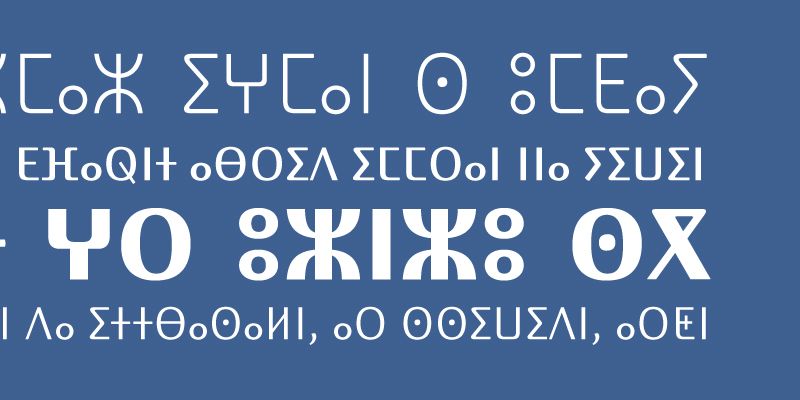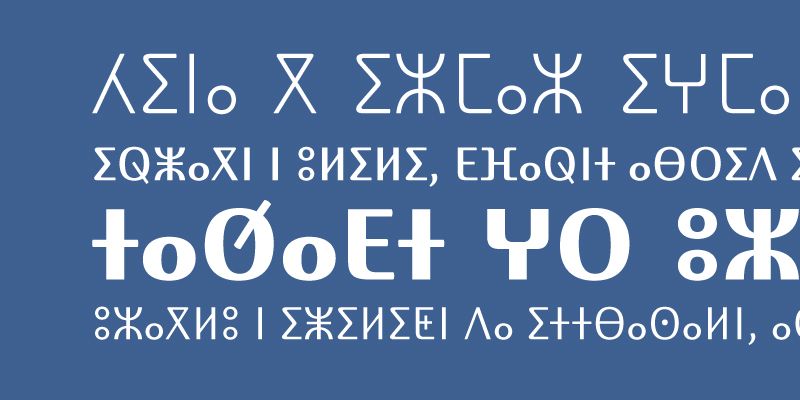
Kigelia Tifinagh hat ein vollständiges Komplement für die nordafrikanischen Sprachen und Dialekte, die diese altertümliche Schrift verwenden. Stilistische Sätze, die alle dokumentierten regionalen orthografischen Varianten abdecken, sind ebenfalls enthalten.